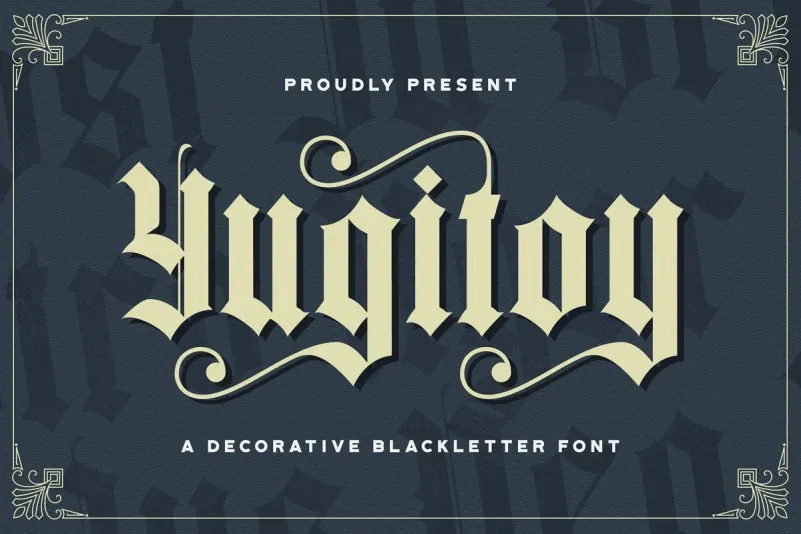
Yugitoy Blackletter Font – Fonte Grátis
Yugitoy Blackletter Font
A Yugitoy Blackletter Font é inspirada em desenhos de cartazes vintage frequentemente encontrados em alguns cafés do Brasil. Ela foi criada e compartilhada pela StringLabs, oferecendo um estilo único e elegante para os designers. Esta fonte vintage victoriana será atraente em uma ampla gama de contextos, dando ao seu design um toque especial e sofisticado. Para aqueles que buscam trazer um toque nostálgico e distinto à suas criações digitais, Yugitoy Blackletter é definitivamente a escolha perfeita.